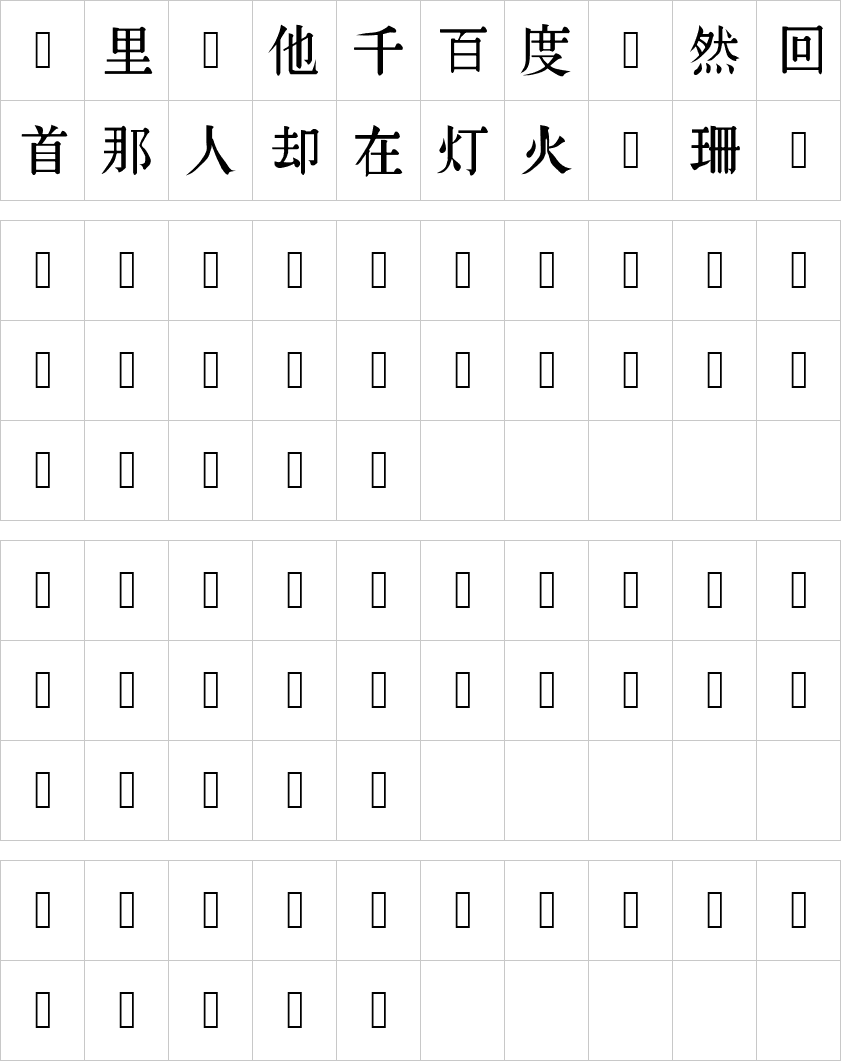
同文新字典体
同文新字典体是从日本古籍《同文新字典》和《 [東京築地活版製造所]活版見本 》复刻而成的一款字体。这款字体的作者是日本的Yoshiki Hayashi,他在Github上建立了这款字体的开源项目,但是却没有提供直接的字体文件,只提供了std文件,要使用字体的话就要自己生成导出。
同文新字典体是一款古籍复刻字体,所以这款主要还是以繁体字为主,包括部分的简体字。